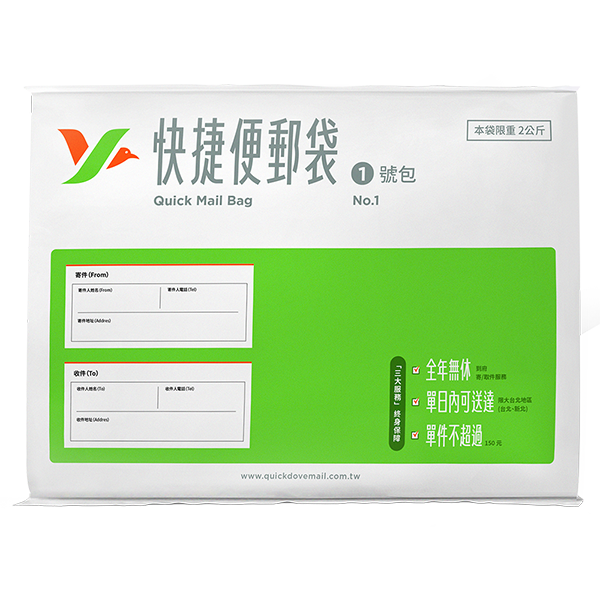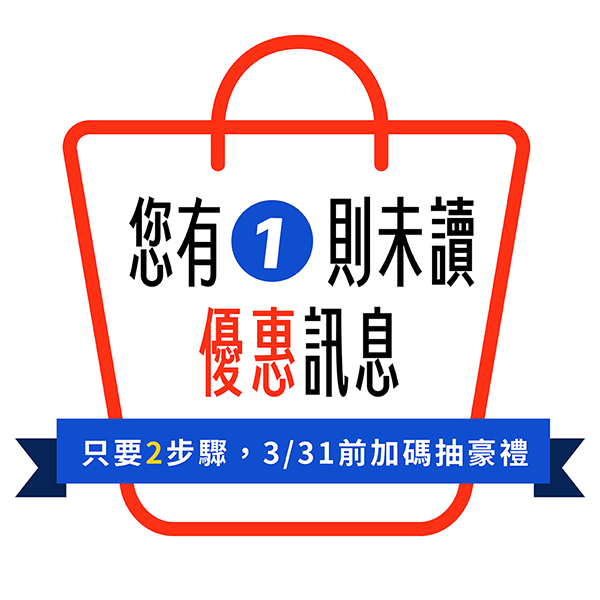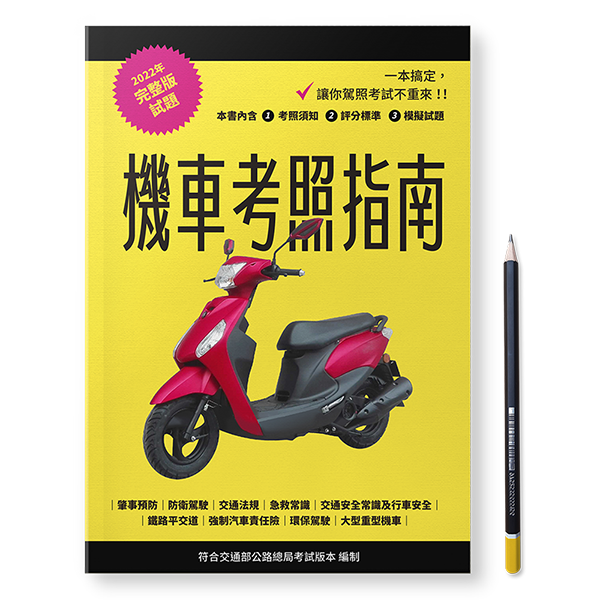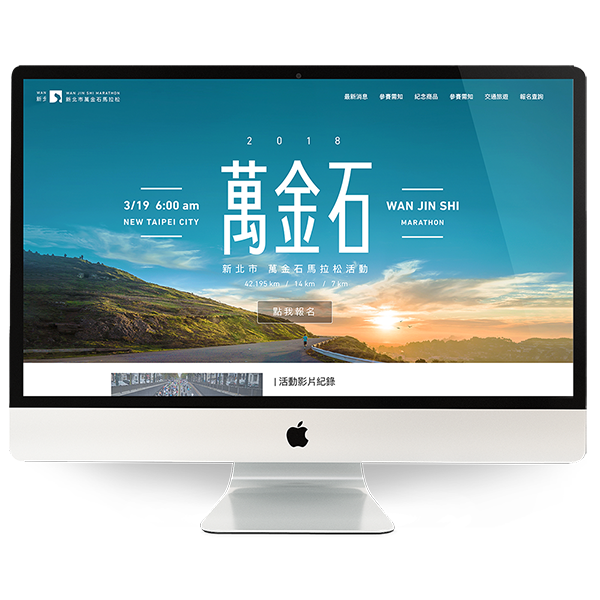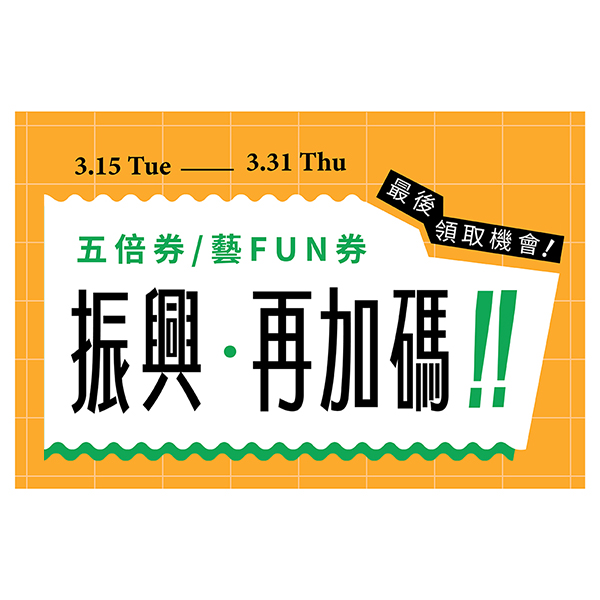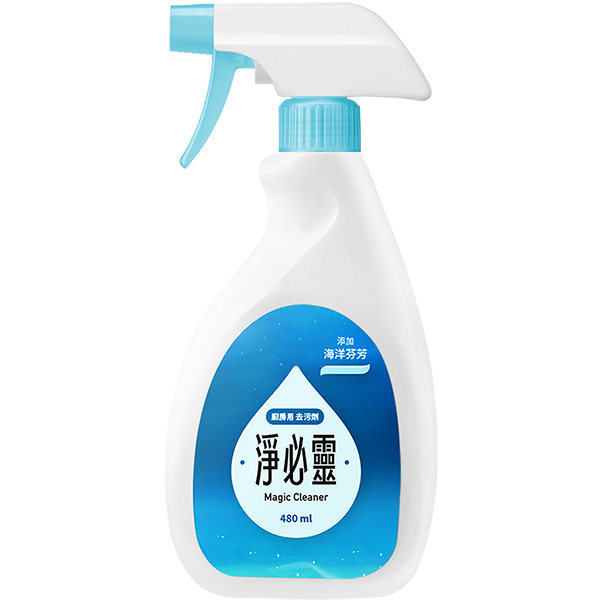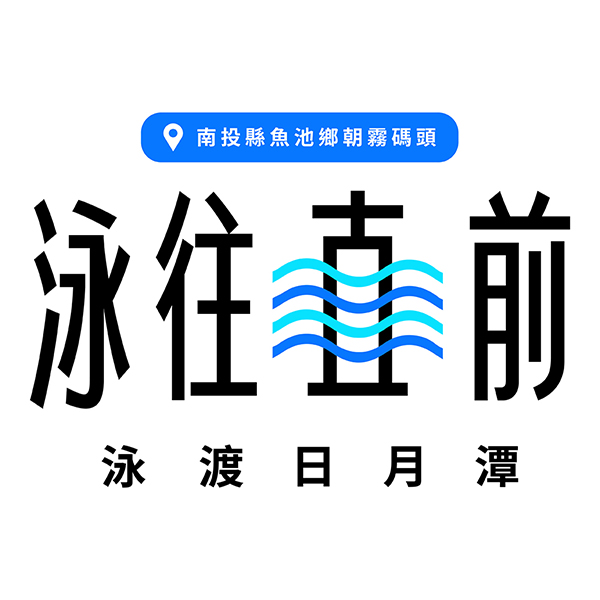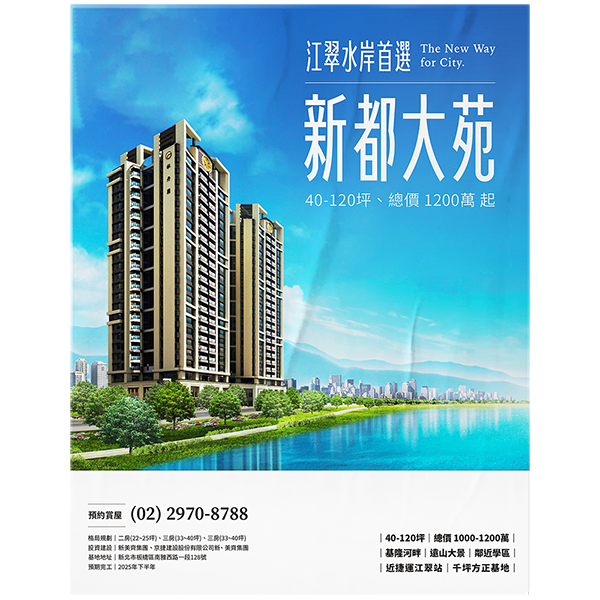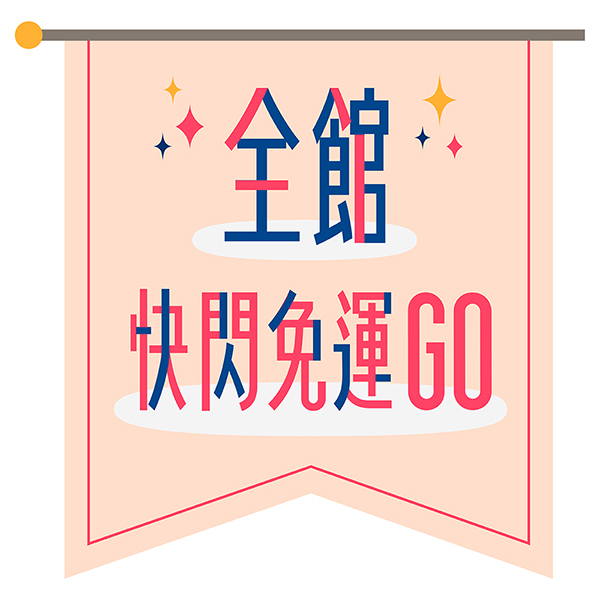
臺灣道路體
源自湯六每天通勤生活中的觀察,
以 6 年時間,落實為完整字體設計。
天然窄體,能放進更多資訊。
- 湯六
字型設計師
湯六
嗨,大家好 ~我湯六啦!!!湯六(aka 勞工楷模)。曾經做過印刷廠美工、攝影棚助理、債務催收人員,本業為電商產業 UIUX 設計師。有一日於上班騎車途中,發現靈感並設計「臺灣道路體」。